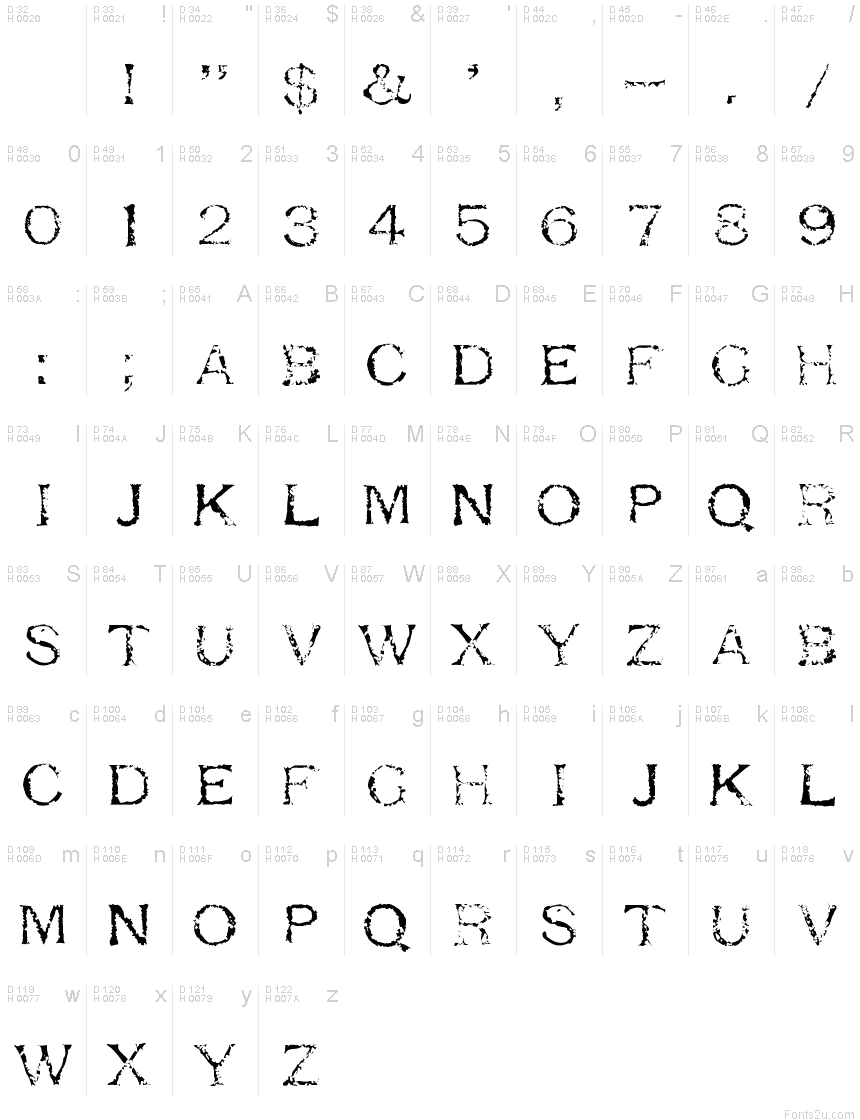
يُعد Respess Capitals Light من l'Abecedarienne خط عرض مجاني بأسلوب الحروف ذات الزوائد (serif) المتآكلة، ويتميز بلمسة عتيقة تحاكي الطباعة القديمة. تبدو الحروف كأنها مأكولة الأطراف، مع انحناءات ناعمة وغير منتظمة ومساحات متآكلة تجعل الحروف تبدو وكأنها بليت بفعل الحبر بدلاً من كونها مرسومة بدقة.
تمنحه هذه الخشونة مكاناً طبيعياً في الملصقات، وأغلفة الكتب، والعناوين، والتغليف، وعناوين التحرير الجذابة التي تتطلب طابعاً خاصاً، حيث يمكن لهذا الخط المجاني إضافة لمسة من العراقة والأجواء بسرعة. يعمل الخط بشكل أفضل في النصوص القصيرة مثل الأحرف الأولى، وعناوين الأغلفة، وتصاميم الشعارات (Logotype)، لأن الحروف الكبيرة المتآكلة تحمل الكثير من الشخصية والقوة بمفردها.